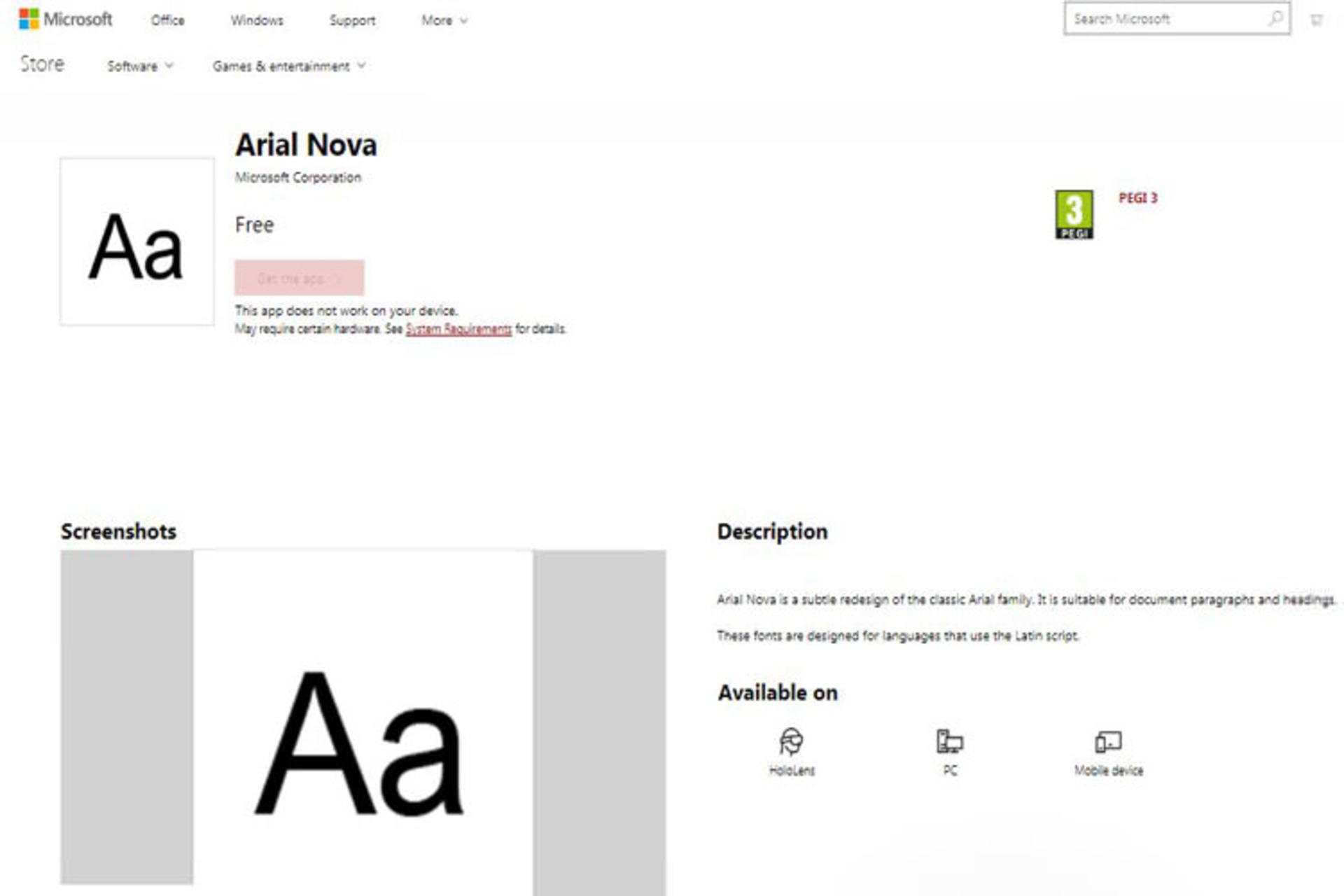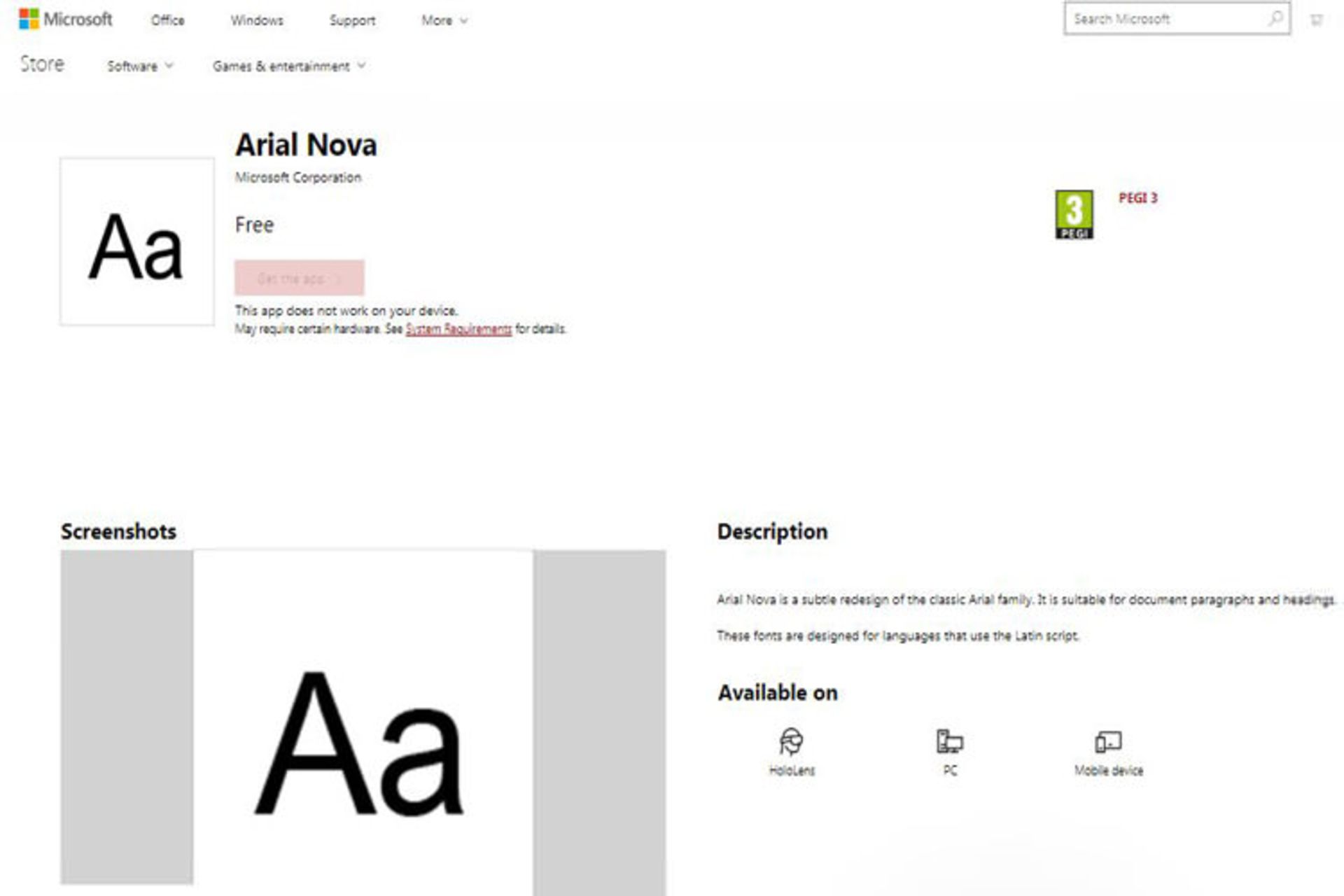
چندی پیش مایکروسافت اعلام کرد که بهزودی کاربران میتوانند بستههای زبان مورد نیاز خود را از مایکروسافت استور دریافت کنند. حال خبر رسیده است که ردموندیها قصد دارند این موضوع را در مورد فونتهای ویندوز نیز پیادهسازی کنند. این خبر نخستین بار توسط کاربری بهنام WalkingCat در توییتر اعلام شد. این ویژگی از امروز با قرارگیری فونت Arial Nova در فروشگاه ویندوز ۱۰ رونمایی شد. این فونت نسخهای بازطراحی شده از خانوادهی فونتهای کلاسیک Arial است و بیشتر در نگارش پاراگرافها و عناوین بهکار میرود.